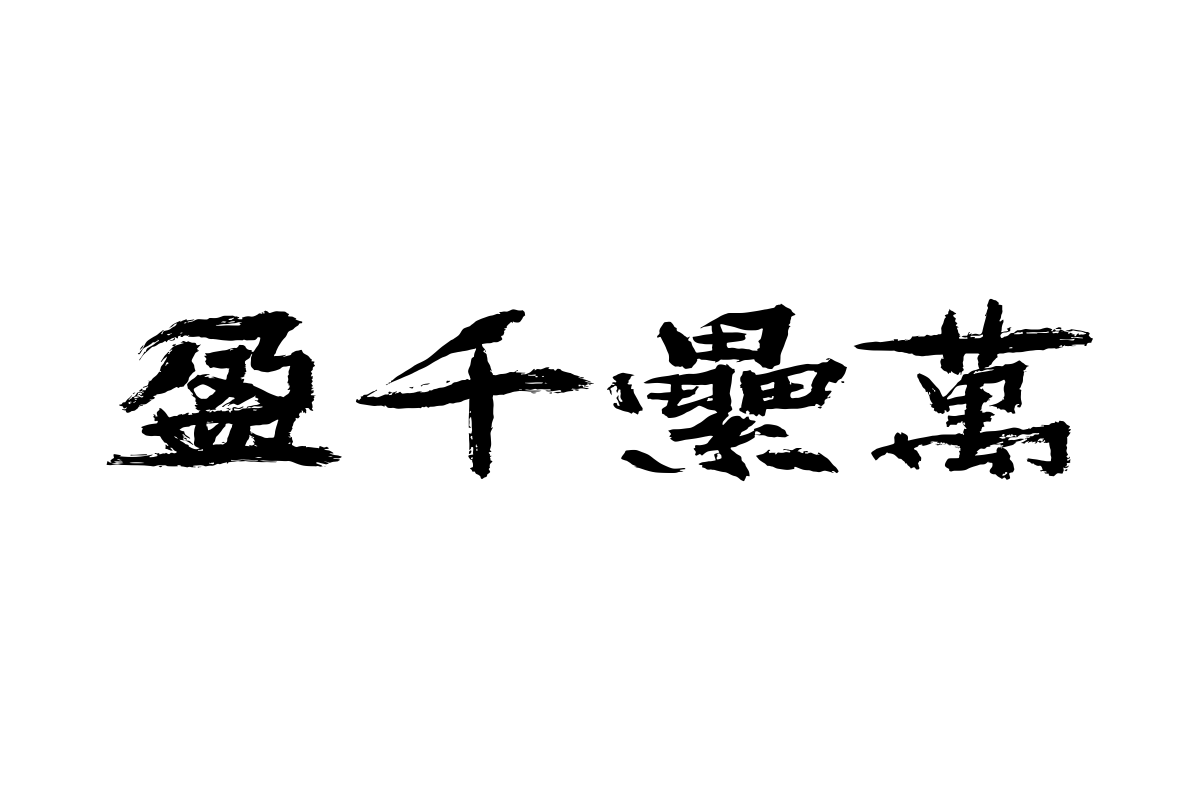
汉仪顺利斗圣繁体是一款由汉仪公司设计的中文字体,具有独特的风格和特点。这款字体采用了传统的书法元素,结合现代设计手法,形成了一种既有传统韵味又不失现代感的字体。
在字形结构上,汉仪顺利斗圣繁体采用了简洁明了的设计,笔画流畅自然,易于阅读和识别。同时,该字体还注重细节的处理,如字间距、行距等方面的调整,使得整体视觉效果更加和谐统一。
在风格上,汉仪顺利斗圣繁体融合了古典与现代的元素,既保留了传统文化的精髓,又符合现代人的审美需求。这使得该字体在各种场合都能展现出独特的魅力,无论是应用于广告宣传、书籍装帧还是网页设计等场景,都能展现出其独特的风采。
总之,汉仪顺利斗圣繁体是一款具有独特风格和特点的中文字体,它不仅能够提升设计作品的美感和质感,还能为使用者带来更好的视觉体验。